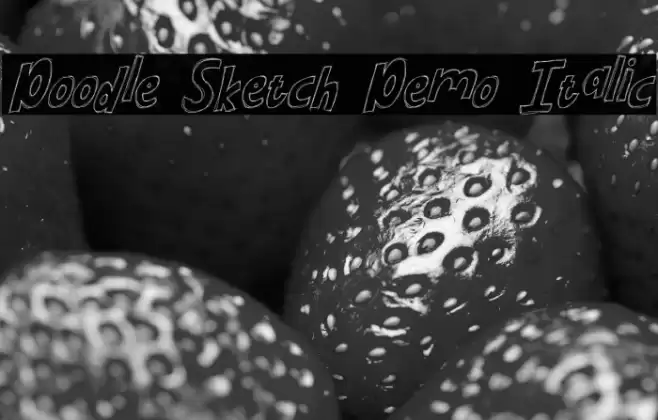
Doodle Sketch Demo Italic Font
| Name | Doodle Sketch Demo Italic |
| Schriften Familie | Doodle Sketch Demo |
| Gewicht | Italic |
| Kategorien | Cartoon |
| Gesamtstil | Playful, Whimsical |
| Anwendungsfall | Headlines, Creative projects, Informal text |
| Vorgeschlagene Projekte | Ideal for children's books, creative branding, informal invitations, and playful designs. |